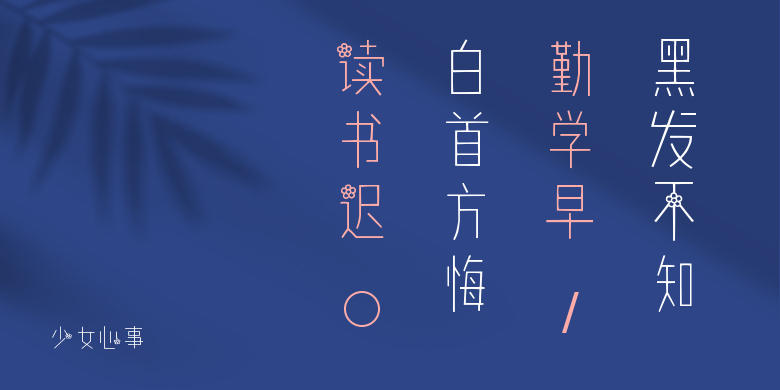
少女心事
少女心事,这款字体结构工整、笔画清晰,兼顾美观与易读性,适用于标题、正文、海报、包装、LOGO 等多种场景。字形优雅稳定,风格百搭耐看,适配日常排版与创意设计,让文字呈现更舒适、更具质感。少女心事一笔一画,皆是细节,以均衡的比例、流畅的线条打造舒适视觉体验,字形端正大气,风格简约现代。无论是商业设计、品牌宣传还是日常排版,都能轻松驾驭,让文字更有格调与力量。少女心事字体下载。